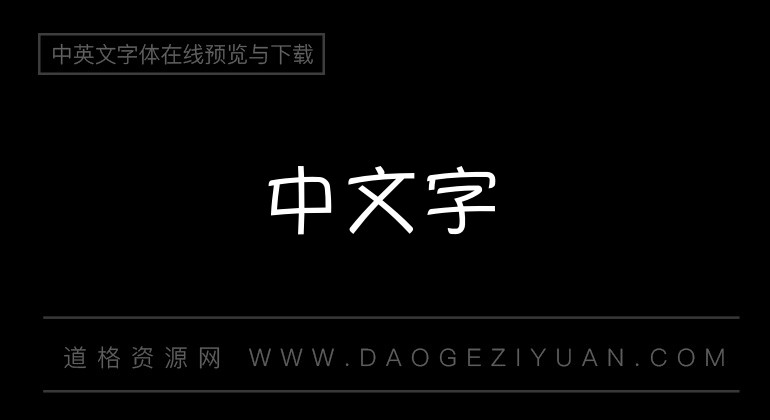
蒙纳繁优皮
蒙纳繁优皮字体是一款经典的繁体中文字体,由蒙纳设计公司推出。它采用繁体汉字,而且每个字的设计都十分优美,充满着古典的风格。这款字体的特点是圆润、精致,字形清晰,极具视觉冲击力,是一款经典的繁体中文字体。它适用于新闻报刊、书籍、杂志、广告等,可以满足不同类型的文字需求。
蒙纳繁优皮是一款非常不错的手写艺术字体,具有很好的视觉感,适合于文化类的宣传设计、商业类品牌的广告和产品包装设计以及个性化文字排版等较多场景。